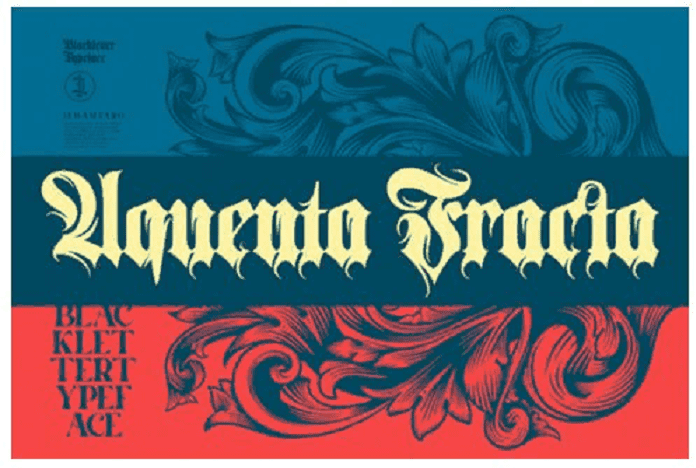
Название: Aquenta Fracta Font (2021)
Aquenta Fracta - это холодный, напористый и отчетливый шрифт с черными буквами, который отлично подходит для передачи любого сообщения с уверенностью, подлинностью и шармом. Он поможет воплотить самые разные идеи, от открыток до брендинга, этикеток и многого другого.
Название: Aquenta Fracta Font (2021)
Aquenta Fracta - это холодный, напористый и отчетливый шрифт с черными буквами, который отлично подходит для передачи любого сообщения с уверенностью, подлинностью и шармом. Он поможет воплотить самые разные идеи, от открыток до брендинга, этикеток и многого другого.